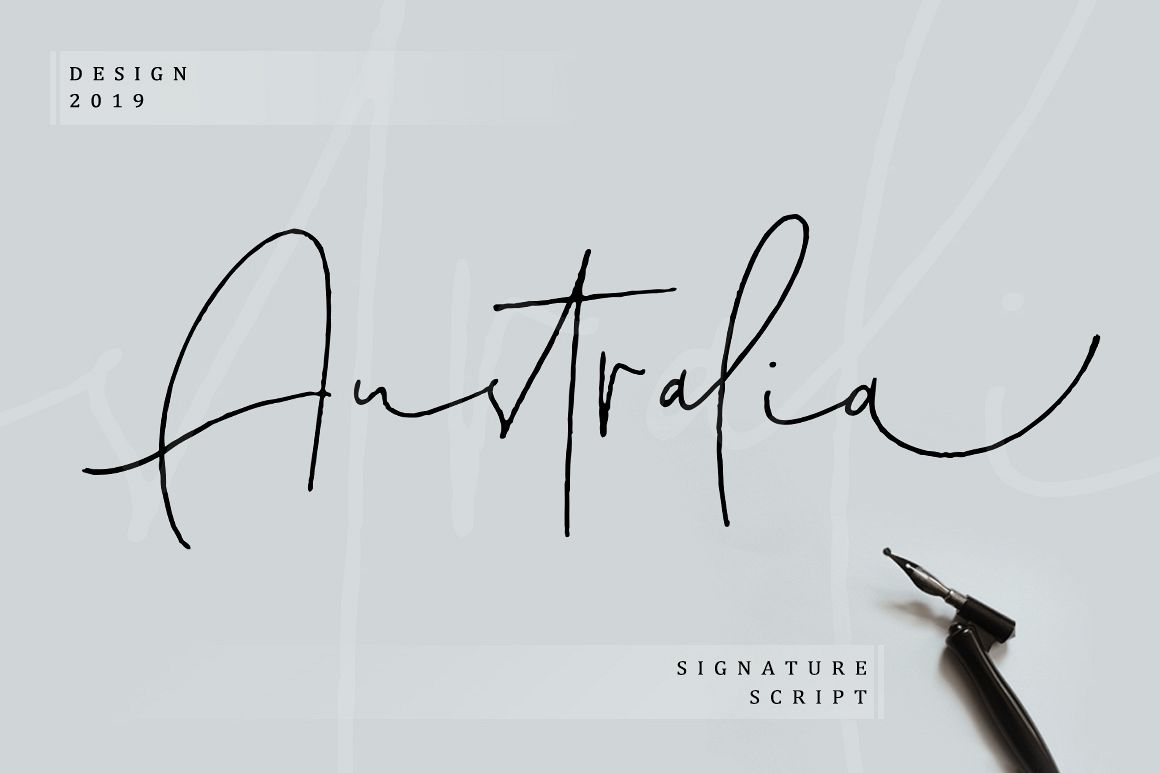
Australia Script
Australia Script  adalah font tulisan tangan monoline yang elegan yang memiliki gaya tanda tangan,
font ini sengaja dibuat dengan pengikat dan alternatif unik.
Australia sangat cocok untuk undangan, kartu ucapan,
berita, pencitraan merek, logo, kartu nama, poster,
kemasan produk, poster blog, dll.